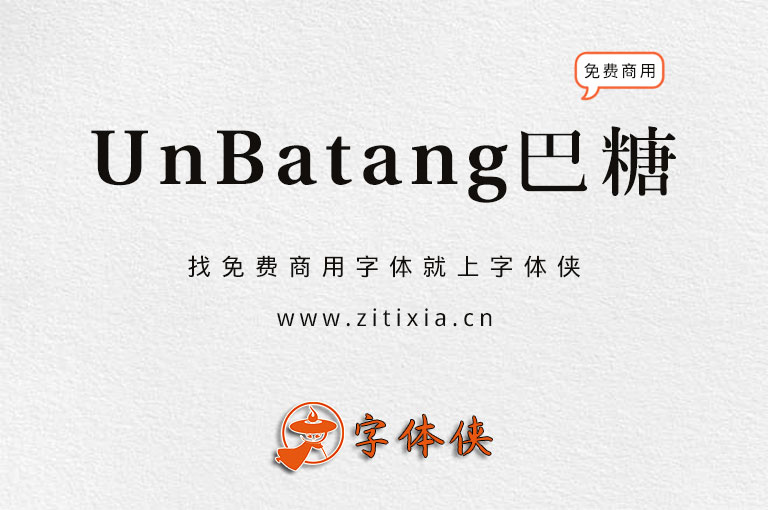
UnBatang巴糖:韩国Un系列开源字体 不一样的韩系汉语文字。
韩国Un系列字体是由@Koaunghi Un于1998年以HLaTeX type1制作而成,作者在20世纪90年代末制作type1字体用于韩国的Tex(JLaTex[1]),并以GNU GPL授权许可进行发布。于2003年,由@Won-kyu Park使用FontForge(PfaEdit)转换成ttf文件进行发布。
韩国Un系列字体包括核心系列9款字体和额外系列10款字体,将会在稍后的时间逐一进行更新。不过较为可惜的是,这系列字体都是以繁体为主,支持简体的字数较少,中国大陆的小伙伴若要使用这套字体会比较难受。